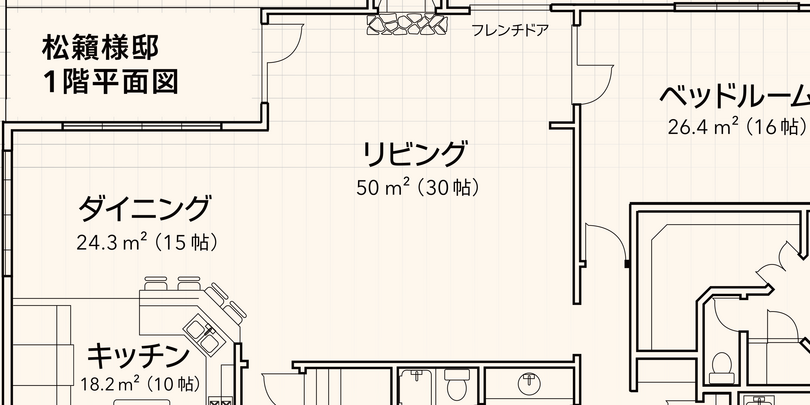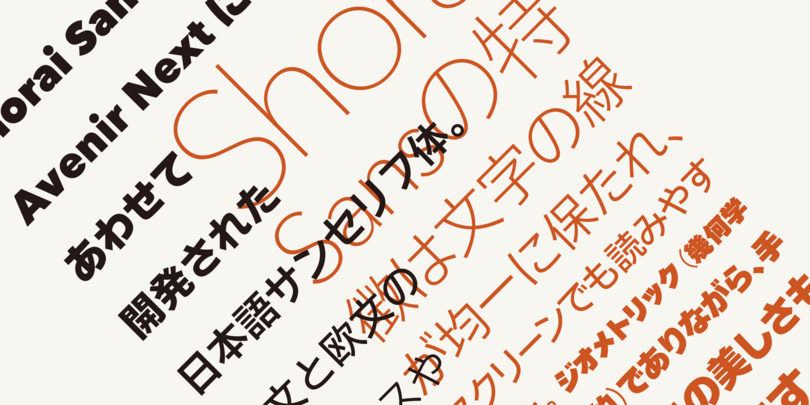
Shorai® Sans : la police sans serif qui ouvre l’horizon de la typographie japonaise.
Nous avons tenté de rendre la graisse Heavy encore plus épaisse qu’une police sans serif japonaise moyenne, et nous avons réduit chaque forme à l’essentiel afin que les formes intérieures paraissent simples. Et voici le résultat – une Sans Serif pour la nouvelle génération.
Akira Kobayashi, Creative Type Director.
Nouveauté du Studio Monotype, Shorai est une police sans serif géométrique conçue par le directeur de la création typographique Akira Kobayashi, les designers typographiques Ryota Doi, Yukihiro Nakamura et Tao Di, et enfin le directeur de la production typographique Robin Hui. Shorai offre une gamme impressionnante de graisses, de l’ultra-light au heavy bold, avec l’une des graisses les plus épaisses actuellement connues au Japon dans les familles sans serif. Shorai est disponible pour tous les clients de Monotype Fonts et est également en vente sur MyFonts.
« Shorai » est un terme dérivé de « Matsukaze », qui signifie « le son du vent soufflant dans les pins ». Lors de la cérémonie du thé, c’est le son de la bouilloire dans laquelle l’eau bout. Avec son nom poétique, cette police évoque l’équilibre entre les subtils coups de pinceau traditionnels dessinés à la main et les contours géométriques nets.
Parfaite pour s’associer avec les polices latines, Shorai® Sans est une police sans serif japonaise dont le design se base sur des éléments d’Avenir® Next. Shorai est particulièrement efficace pour les créatifs qui cherchent l’harmonie entre les langues dans une communication internationale. Jusqu’à présent, assembler les apparences des informations japonaises et occidentales a été un défi majeur dans la typographie japonaise. Shorai, et précédemment la police Tazugane de Monotype, offrent des solutions véritablement internationales pour combiner des typographies CJK avec des polices latines classiques.
M. Yukihiro Nakamura est un créateur légendaire de typographies au Japon. Dans les années 70, il est à l’origine d’un changement sismique dans le domaine du design typographique, avec le design de deux Sans Serif qui ont bousculé les idées préconçues sur les polices sans serif au Japon. De la même manière, basée sur les principes de la conception universelle, avec ses formes de lettres simplifiées et sa vaste gamme de graisses, Shorai ouvre un nouvel horizon à la typographie japonaise.
« Je peux dire que ce que nous avons fait était, fondamentalement, de repousser les limites et d’avancer de manière expérimentale », explique le directeur de la création typographique Akira Kobayashi. « Nous avons tenté de rendre la graisse Heavy encore plus épaisse qu’une police sans serif japonaise moyenne, et nous avons réduit chaque forme à l’essentiel afin que les formes intérieures paraissent simples. Et voici le résultat – une Sans Serif pour la nouvelle génération. »
Dans la plupart des polices sans serif conventionnelles au Japon, presque toutes les terminaisons des traits sont visibles, même dans les graisses les plus épaisses. En contraste, la plupart des fins de traits de Shorai se fondent dans les traits adjacents pour obtenir des formes intérieures simples. La famille de police statique Shorai comporte dix graisses de Ultra Light à Heavy. La variation Heavy est l’une des plus épaisses parmi les familles de polices sans serif japonaises actuellement connues. Les graisses de milieu de gamme de Shorai sont un choix idéal pour les corps de texte autant que pour la signalétique publique. La police variable, quant à elle, permet une large expression et offre aux designers de l’espace pour expérimenter tout en fournissant aux marques une boîte à outils pratique avec une gamme de polices statiques.
Quand les 400 kanjis de base ont été complétés, une rencontre entre les générations et les cultures a permis pendant une semaine de rassembler les idées pour créer, ensemble, un système calligraphique. C’est à Hong Kong que se sont réunis les designers et les ingénieurs typographiques de Monotype (venant du Japon, de Hong Kong et d’Allemagne), ainsi que M. Nakamura.
« Les idées de M. Nakamura sont toujours novatrices, surprenantes et excitantes », explique Ryota Doi, designer typographique. « Cette police, fruit d’une collaboration de plusieurs générations, est géométrique, mais elle traduit d’une certaine manière le mouvement de la main de l’homme. Shorai Sans dépeint un avenir entouré d’autres personnes. »
Shorai® Sans. La voix de l’essentiel.
Akira Kobayashi, Ryota Doi et Yukihiro Nakamura dessinent Shorai Sans.